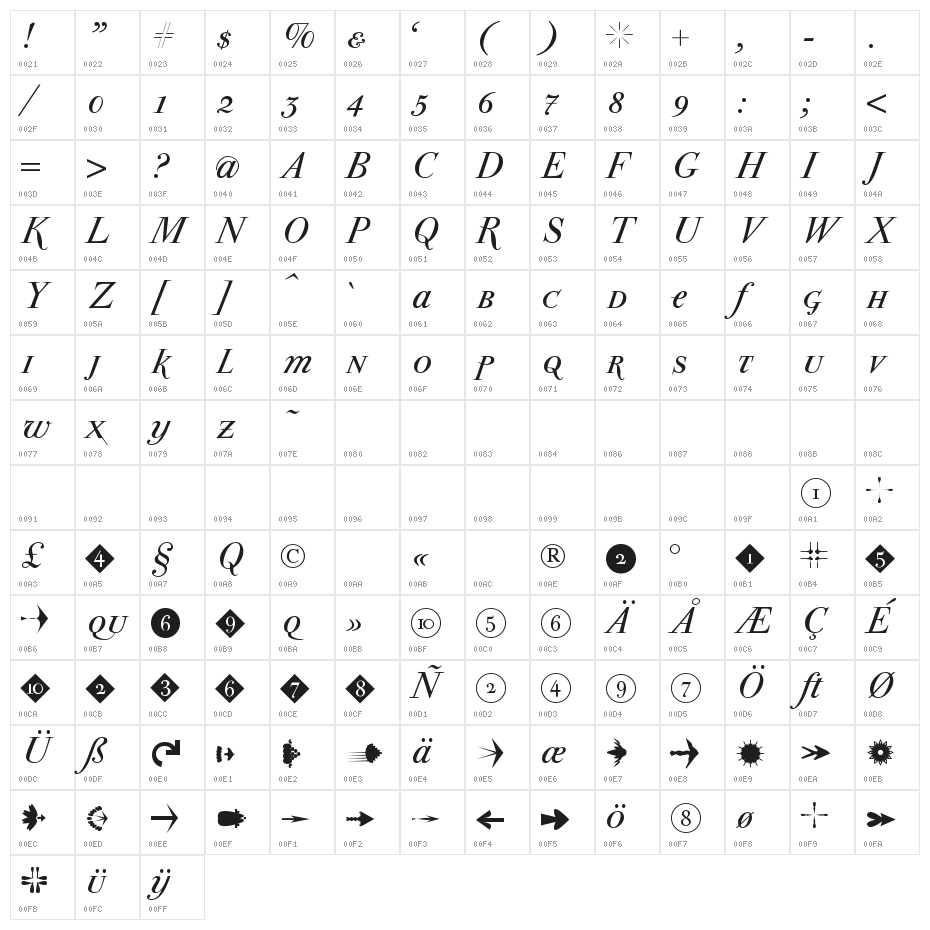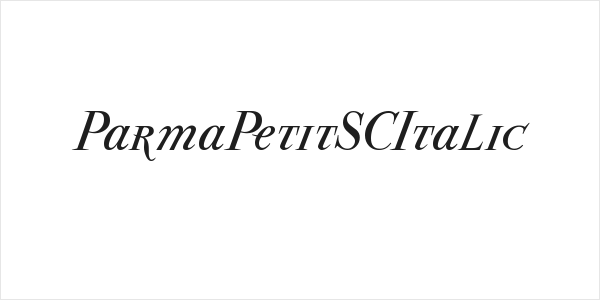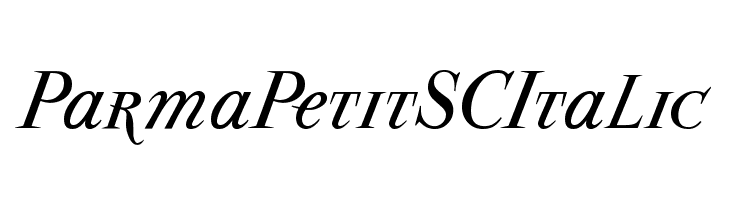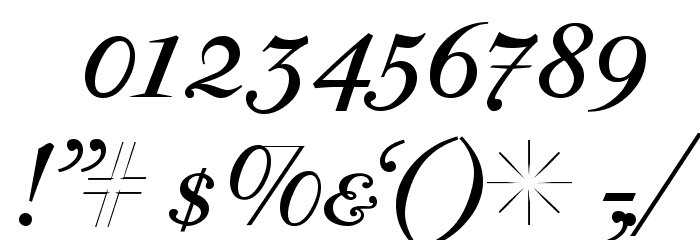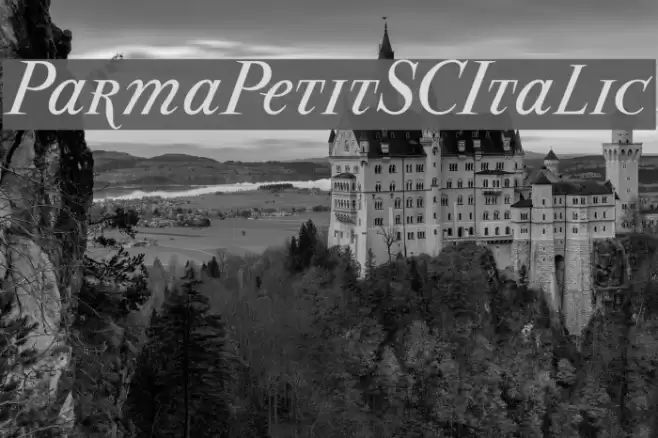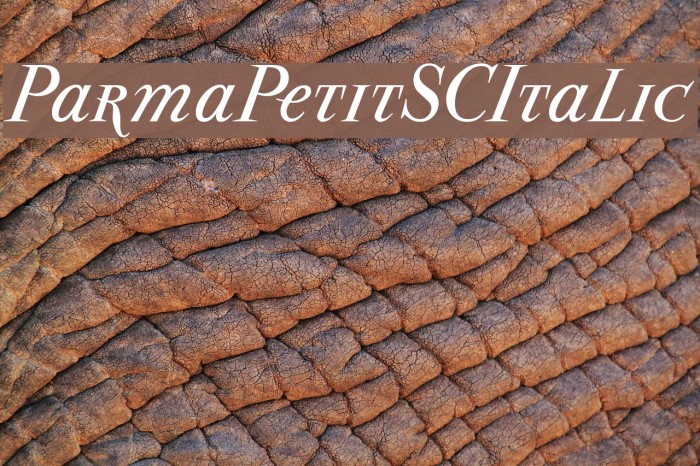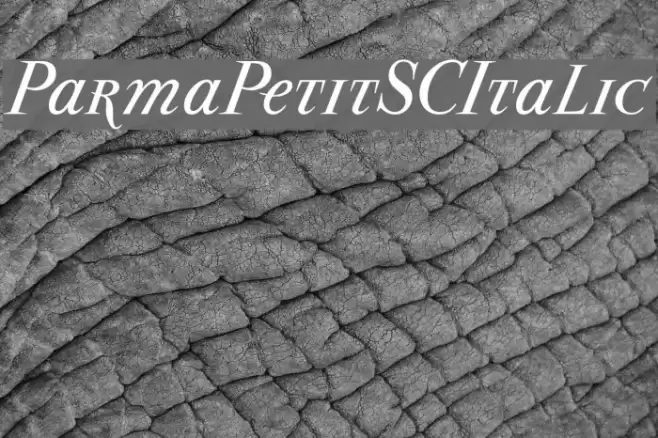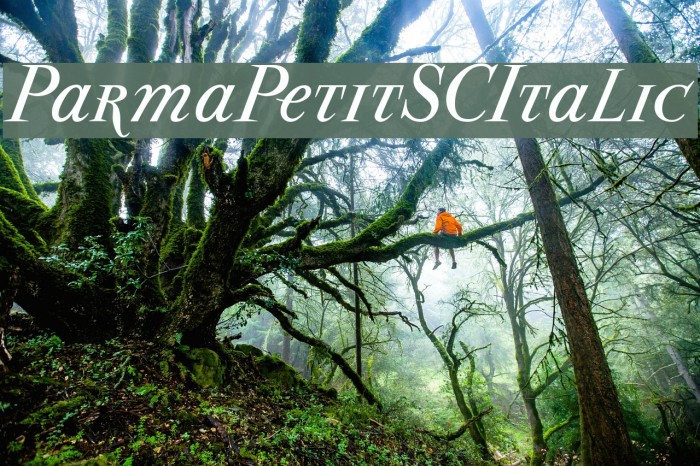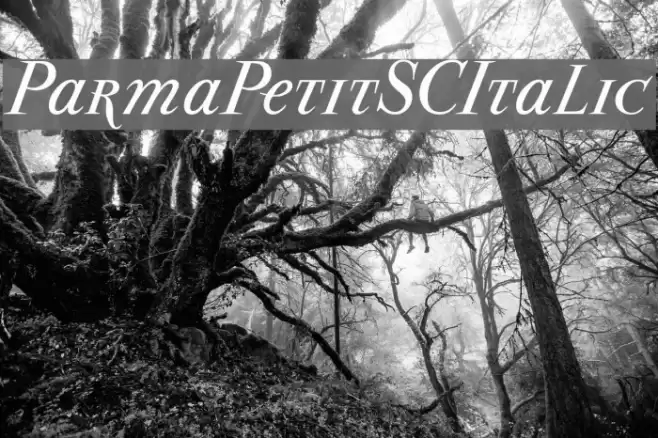
ParmaPetitSCItalic Font
يتضمن هذا الخط 195 حرفًا. انقر على أي حرف لرؤية التفاصيل.
| النمط العام | Classic |
| حالة الاستخدام | Headlines, Body text, Logos |
| مشاريع مقترحة | Ideal for projects requiring a touch of elegance, such as wedding invitations, formal event programs, luxury branding, and editorial design. |